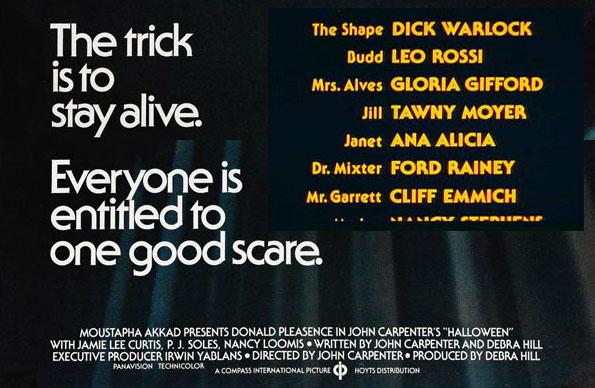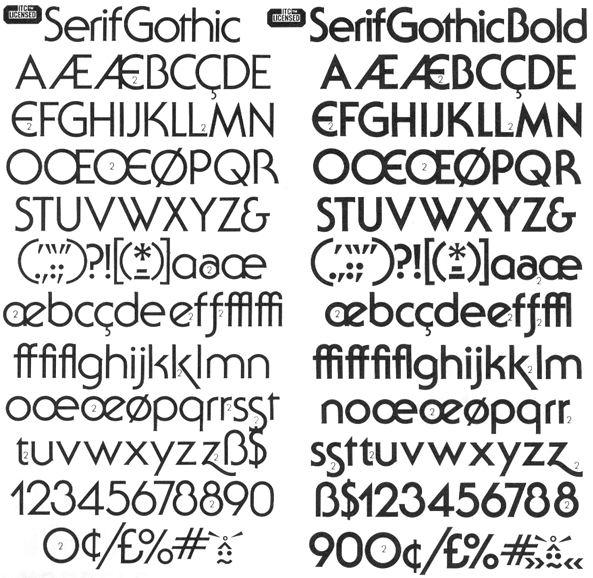
Titletext aus HALLOWEEN II (1981) von John Carpenter
Ich suche mal wieder eine Geometrische, diesmal zwischen Bauhaus und Kabel pendelnd. Es muss sie schon in den 80er Jahren gegeben haben. Auffallend sind bei den Versalien das keck nach vorn schreitende R und das  W mit Orientierung nach links. In den Gemeinen wird stark gerundet und ein paar Füßchen weggelassen.
Typographica und The Luxx weisen Parallelen auf, ich wüsste aber gern, welche Schrift damals bei MGM im Original verwendet wurde.
Leider verweisen alle Fundstellen immer nur auf ITC Serif Gothic für das Logo. Die sehr prägnante andere Schrift bleibt unerwähnt.
Ich sehe gerade, dass mindestens zwei Schriften am Werk sind. Bei einer ist der Mittelstrich vom "e" gekippt. Ausgangspunkt meiner Suche war die gelbe Schrift in die Title-Box. Die Version von "The trick ist to stay alive" möchte ich nun aber ebenfalls gern wissen.
Zweiter Nachtrag:
Die weisse Schrift orientiert sich doch sehr stark an Serif Gothic. Nur eben ohne Serif und mit einem Antiqua-a. Das ist mir vorher entgangen.
Ohje ohje. Hab schlecht hingeschaut. Es ist doch ITC Serif Gothic Bold. Nun wäre also nur noch die gelbe Schrift zu suchen.
Der Thread kann eigentlich gelöscht werden. :D  ITC Serif Gothic hat bis zum Heavy-Schnitt das gesuchte W und dürfte somit auch für die gelbe Schrift hingehalten haben. Ich muss mir also nur noch über die Sonderfiguren Gedanken machen.
Das mit der Serif Gothic scheint zu stimmen. Die Serifen wurden vielleicht auf dem langen Weg durch die Technik abgeschliffen? Gab es ggf. ein alternatives „a“?
Es gibt gemäß der Seite auch Versionen des Plakats mit einer abweichenden Schrift, welche durchaus die Original ITC Serif Gothic sein könnte.
Auch die Zeit passt recht gut. Du kannst notfalls mit einer der Grafiken eine Schriftensuchmaschine füttern und dann schauen was noch raus kommt? Bei der anderen Schrift klingelt es, aber ich finde keinen Einstieg in meinen Unterlagen. Josephine Sans ... die baut auf solche Schriften auf ... aber da komme ich jetzt auch nicht weiter ...
Ich habe schon mehrfach Anläufe genommen geometrische Schriften dieser Art (ganz besonders das große W) zu suchen und zu dokumentieren. Ich bin aber nie weit gekommen. Vielleicht klappt es dieses Mal?
Die Serifen wurden vielleicht auf dem langen Weg durch die Technik abgeschliffen?
Genau das hatte mich auf eine falsche Fährte gelockt.
... abgeschliffene Serifen bei der ITC Serif Gothic ...
Genau das hatte mich auf eine falsche Fährte gelockt.
Das ist „die“ Kernkompetenz dieser Schrift. Von den Letterformen erwartet man eher eine Serifenlose als eine Antiqua. Wenn dann die Serifen auch nur leicht an- und abgeknabbert werden, erscheint diese Schrift wie eine geometrische Serifenlose. Ich kenne sonst keine Schrift die das so perfekt kann. Die Copperplate Gothic geht zwar auch in diese Richtung, ist aber davon noch weit entfernt.
Ich finde sie auch wirklich wunderschön und werde sie mir zulegen, aber wenn man erstmal Serifenlose mit gedrehtem e sucht, kannst du dir vorstellen, was das für eine Irrfahrt war.